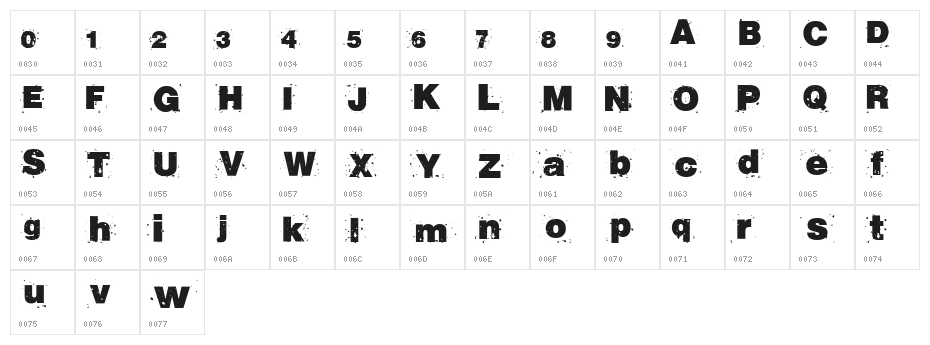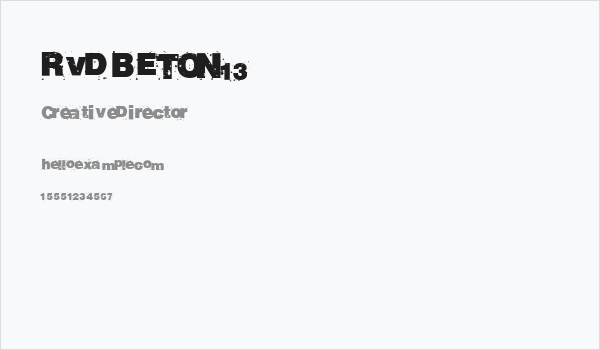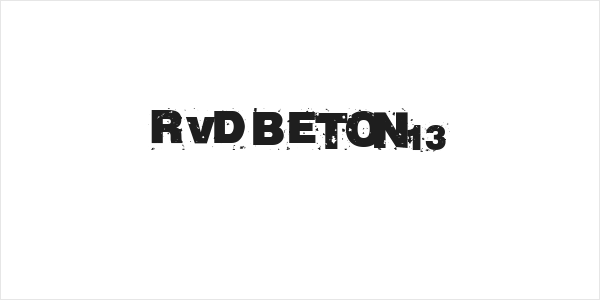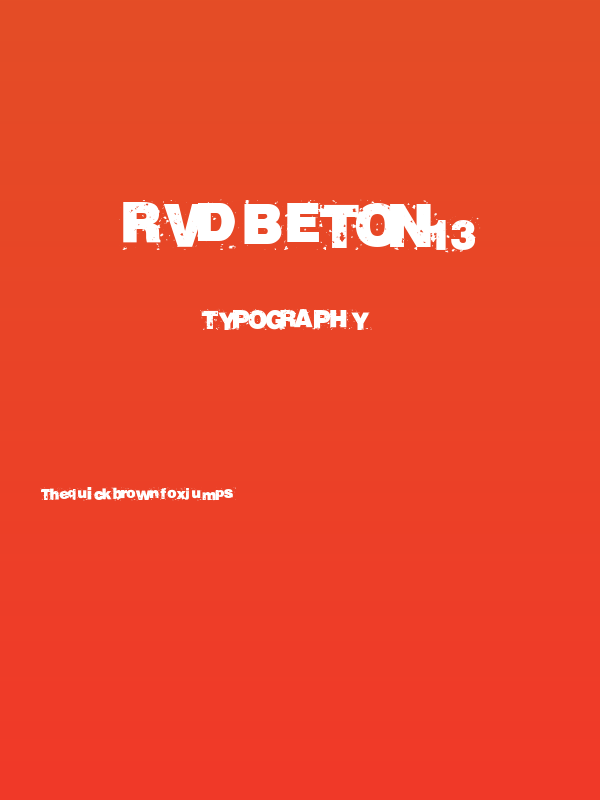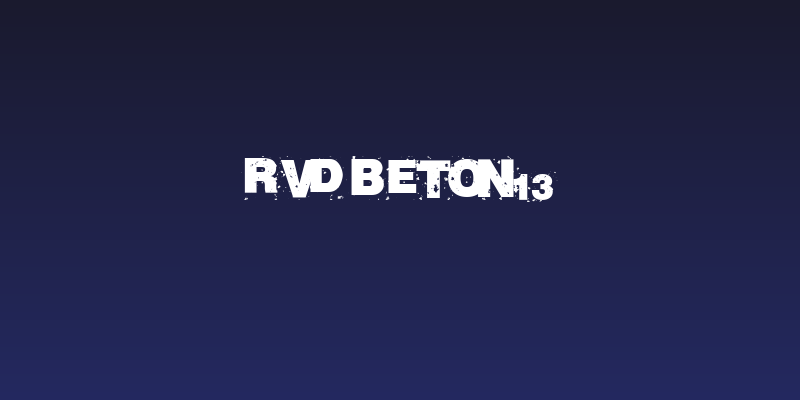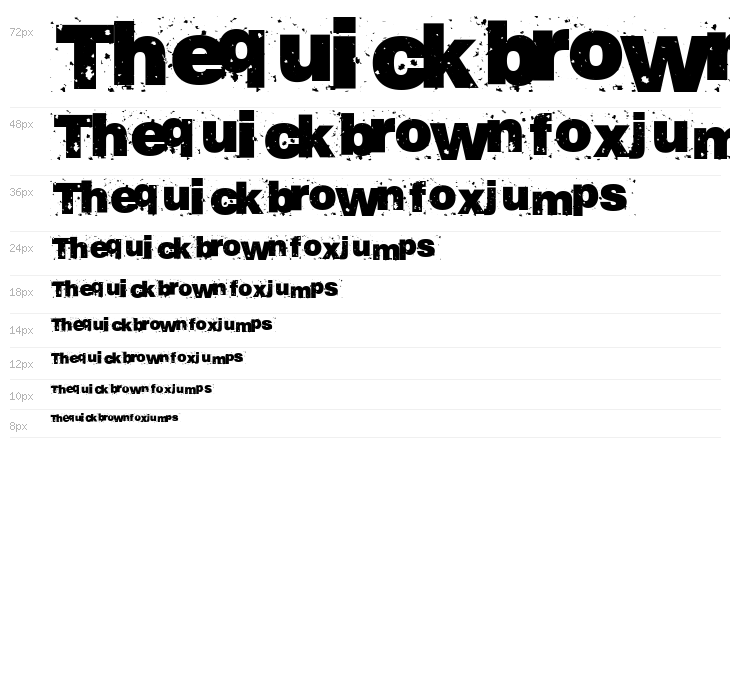
RvD_BETON13 Font
| Stile generale | Industrial, Edgy, Rugged |
| Progetti proposti | Ideal for posters, album covers, urban-themed designs, and branding projects that require a strong, edgy look. |